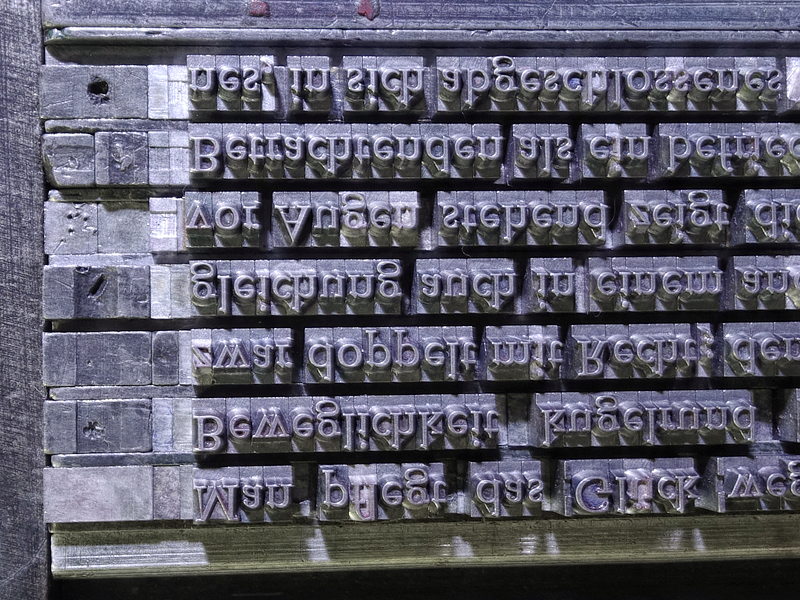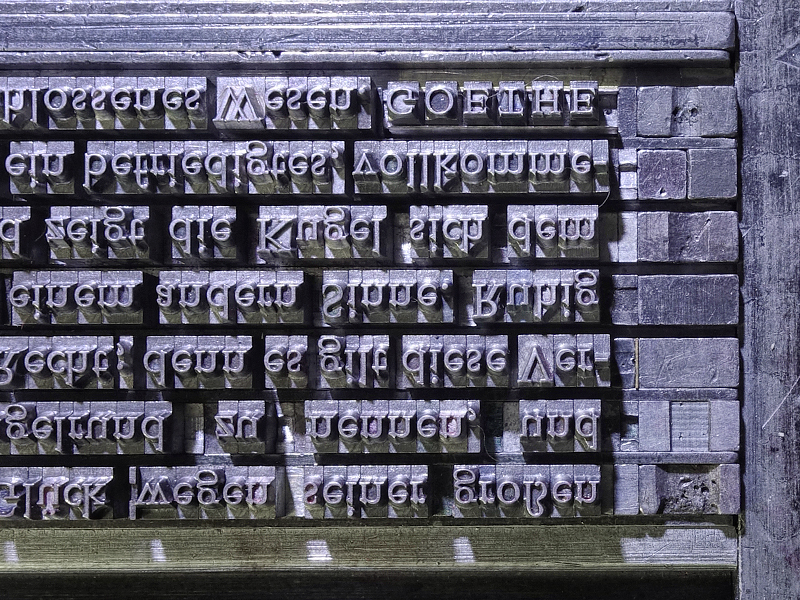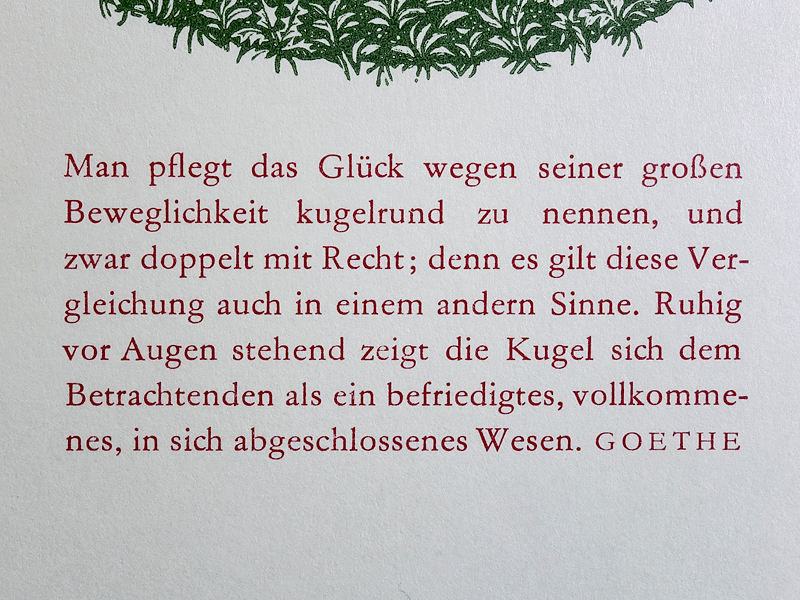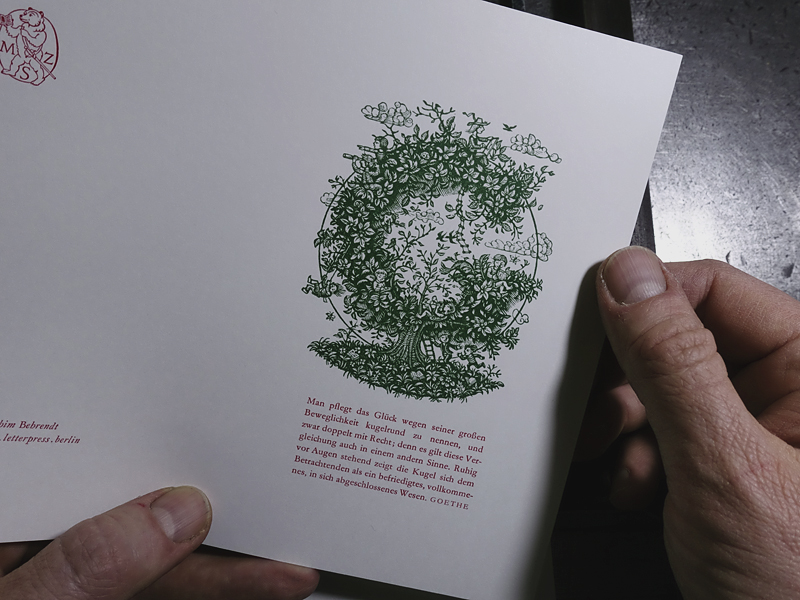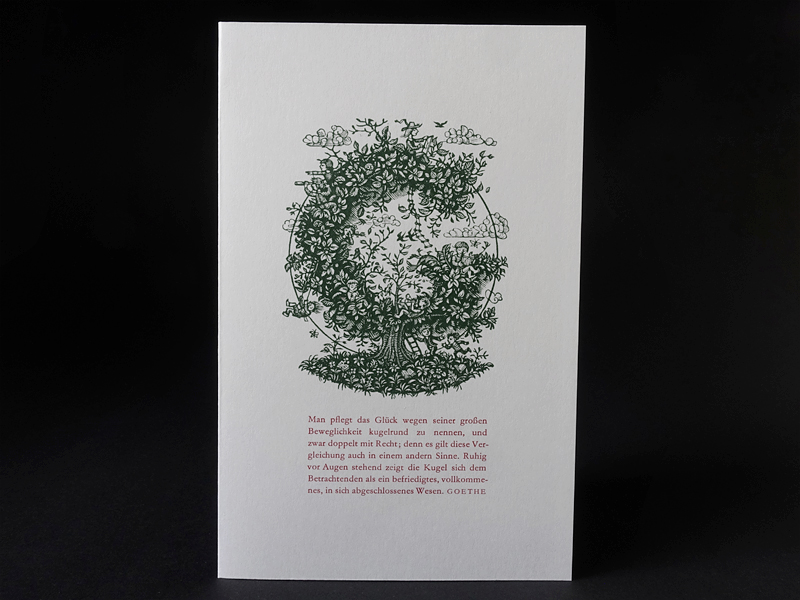
Der Randausgleich im Bleihandsatz
Man kann schlecht winzige Spatien, also nichtdruckende Teilchen, vor die Zeilen legen, weil diese bei der Verarbeitung der Kolumne allzu leicht abfallen würden. Wie hier im Bild gezeigt (unten), werden größere nichtdruckende Quadraten und Spatien verwendet. Auf der linken Seite der Kolumne ist nur das »v« ein wenig (einen halben Punkt) aus der Satzkante herausgezogen. (Der Satz steht kopf, weil wir Schriftsetzer ihn von links nach rechts lesen. Aus »oben« wird »unten«.)
Auf der rechten Seite sind es zwei Bindestriche, die aus der Satzkante herausgeschoben wurden. In der Vergrößerung fällt das sogar auf, obwohl es sich nur um eine Verschiebung von anderthalb Punkt handelt – das ist ein guter halber Millimeter. Auffallen soll der Randausgleich niemandem. Um zu beurteilen, ob der Randausgleich gelungen ist, muß man den gedruckten Text in Originalgröße anschauen und keine Makroaufnahmen vom Satz. Es handelt sich um die Garamond von Typoart im Grad Petit, also 8 Didot-Punkt. Die Versalien am Ende sind aus Nonpareille (6 Punkt) gesetzt.
Deshalb steht hier noch ein Foto, das den ganzen Druckbogen mit den Händen des Druckers zeigt.
Der Randausgleich ist gelungen, wenn an der Satzkante weder Dellen nach innen noch Spitzen nach außen auffallen.
Bei der Grafik handelt es sich um einen Holzstich von Hans-Joachim Behrendt. Eine animierte Typografie gewissermaßen, das G als belebter Baum. (Dazu mehr im Blog aus meiner Werkstatt.)